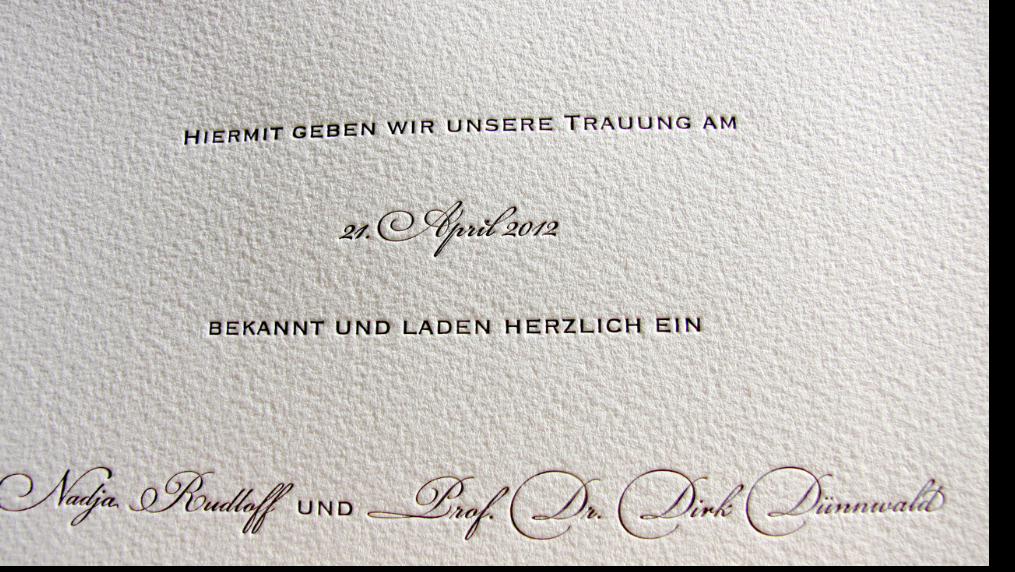
könnt ihr mir vielleicht bei der Identifizierung der beiden verwendete Schriften helfen? :-)
Die geschwungene Schrift müsste leider eine andere sein. Hast du vll noch eine Idee?